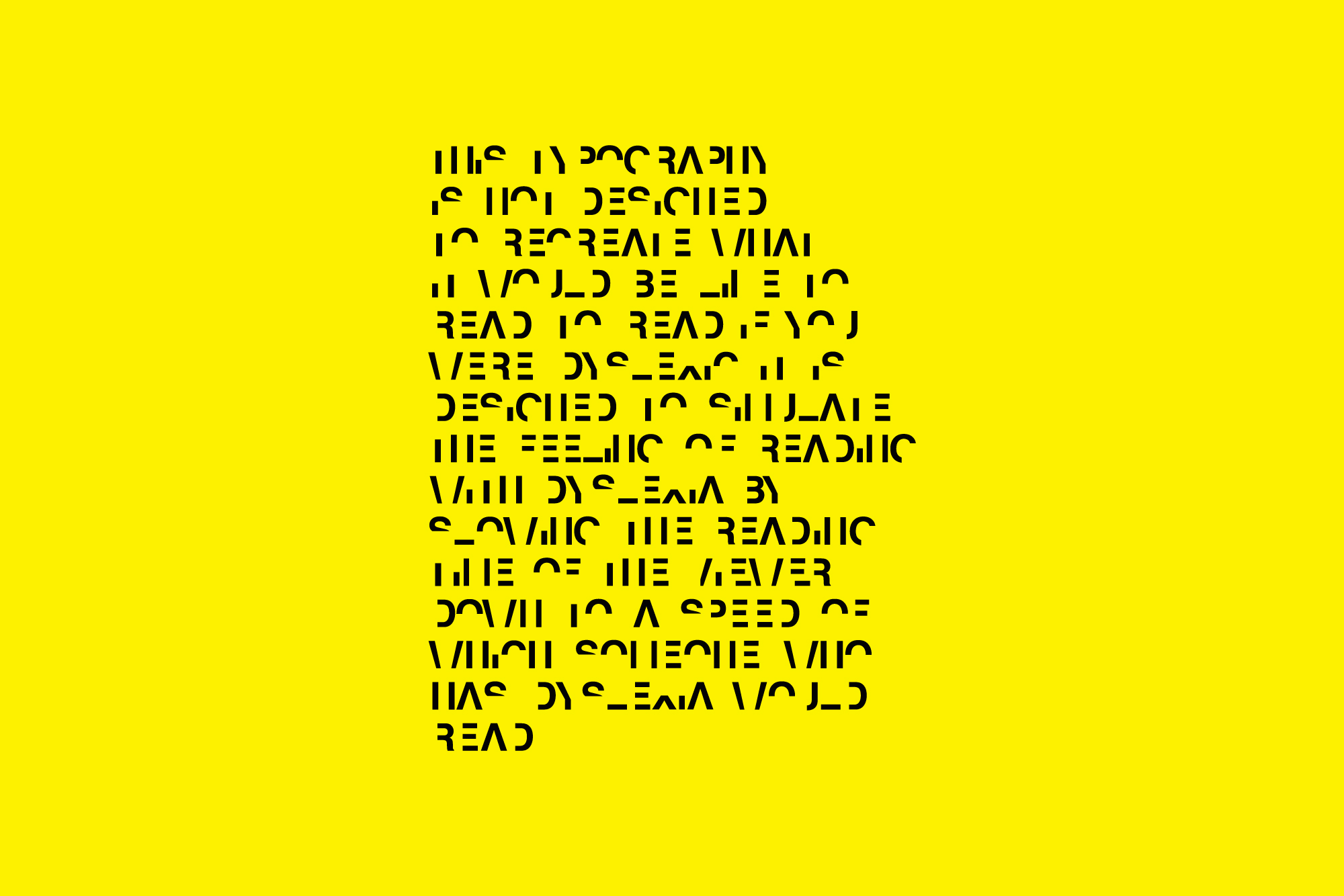
La dislessia si manifesta con la difficoltà di comprendere testi scritti, esistono però font per dislessici, dei particolari caratteri che rendono più leggibile il testo per chi soffre di questo disturbo. Tra i DSA, ossia Disturbi Specifici dell’Apprendimento, la dislessia è la più comune in bambini e ragazzi.
Se volete avere un’idea della difficoltà di lettura che può avere un dislessico, il designer britannico Dan Britton ha creato un font “al contrario”, ovvero un font a cui manca il 40% di ogni lettera. In verità questo font non riproduce esattamente quello che un dislessico percepisce, ma rende l’idea di come possa essere difficoltosa e lenta la lettura.
Esiste ad oggi una vera e propria guida, redatta dalla British Dyslexia Association, un associazione con sede a Bracknell, in Inghilterra. Questa guida racchiude le indicazioni stilistiche per la creazione di materiale didattico che faciliti l’apprendimento per chi ne soffre.
Tra le varie indicazioni c’è proprio un vademecum su come deve essere il font utilizzato: la grandezza delle lettere, la crenatura e l’interlinea. Una particolare attenzione va posta ai grafemi simili, come nelle lettere p e b, facilmente confusi dai dislessici.
Quali sono i migliori font per dislessici?
Tra i font che troviamo normalmente sui programmi di videoscrittura, quelli più ad alta leggibilità sono sicuramente: l’Arial, il Comic Sans, l’Helvetica, il Tahoma, il Trebuchet e il Verdana. Ma se vogliamo ottenere un risultato migliore ci si può affidare a font studiati appositamente per il disturbo della dislessia.
Tra i vari font è stato realizzato l’EasyReading, nato da anni di ricerche affiancate da studiosi del disturbo dislessico. Il carattere è molto particolare perché “ibrido” tra il serif e il sans serif, è realizzato infatti con la combinazione di lettere dotate di grazie (serif) e lettere senza grazie (sans-serif), unico quindi nel suo genere.
Le grazie, in particolare, sono state realizzate apponendo specifici allungamenti ortogonali alle estremità delle lettere, impedendo così la confusione di quelle simili per forma. Mentre i caratteri ben distanziati impediscono la percezione di affollamento.
Bianconero è invece una casa editrice che ha realizzato un suo font specifico per creare libri ad alta leggibilità. Grazie ad un team composto da graphic designer e psicologi della sfera cognitiva, hanno studiato ben nove collane narrative per bambini delle elementari fino ai giovani adulti.
Il font Dyslexie è frutto del lavoro di un olandese affetto dalla dislessia, ogni lettera è unica e inequivocabile, dallo stile un po’ infantile. Mentre OpenDyslexic si pone come carattere opensource, ha lettere diverse, alcune più evidenziate rispetto ad altre per creare testi facilmente leggibili.
Se non siete sicuri che il vostro font superi i requisiti per la dislessia, potete testarlo sul sito testmefont.com. Il sito permettere di fare pratica con i requisiti minimi per creare font ad alta leggibilità.
Solo il font fa la differenza?
A rendere leggibili i font per dislessici però non è solo il tipo di carattere utilizzato, che deve comunque essere impostato tra i 12 e i 14 punti. Se parliamo di testo stampato gioca un ruolo importante anche la carta utilizzata, che non deve essere lucida, ma opaca per non riflettere la luce. Il suo peso deve essere intorno ai 90 grammi per evitare trasparenze fastidiose, che potrebbero ulteriormente confondere. Il colore di fondo aiuta a evidenziare in modo migliore le parole, l’ideale è il bianco crema, ma è anche utile un’impaginazione ordinata e spaziosa.
L’interlinea utilizzata deve essere di 1,5 o doppia, le frasi brevi (con un massimo di 70 caratteri) e paragrafi corti per sottolineare meglio le parti di testo. Può essere utile poi utilizzare il grassetto per le parole importanti, mentre l’allineamento è consigliato a sinistra.